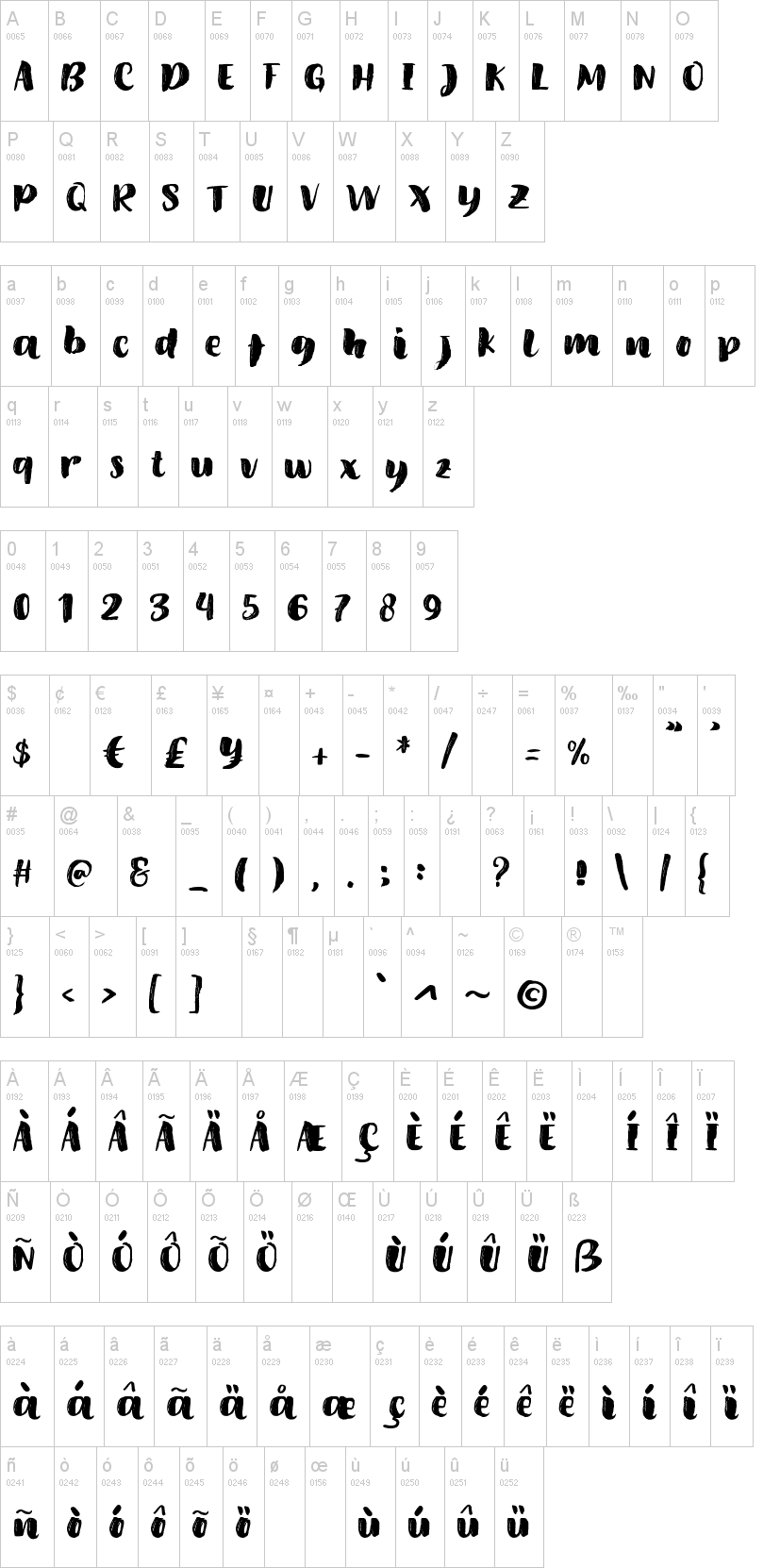
Amel Brush
Amel Brush 是一种手写风格的字体,具有自然、流畅、生动的特点。它的笔画粗细不一,有一种生动、有活力的感觉。Amel Brush 字体非常适合用于设计海报、广告、宣传品或其他需要强调视觉效果的设计项目。它可以让文本看起来更加有趣、有吸引力,同时也能够展现出您的创造力和个性。此外,Amel Brush 字体也提供了多种字重和格式,可以根据不同的设计需求选择不同的字重和格式。
Amel Brush是一款非常不错的手写艺术字体,具有很好的视觉感,适合于文化类的宣传设计、商业类品牌的广告和产品包装设计以及个性化文字排版等较多场景。